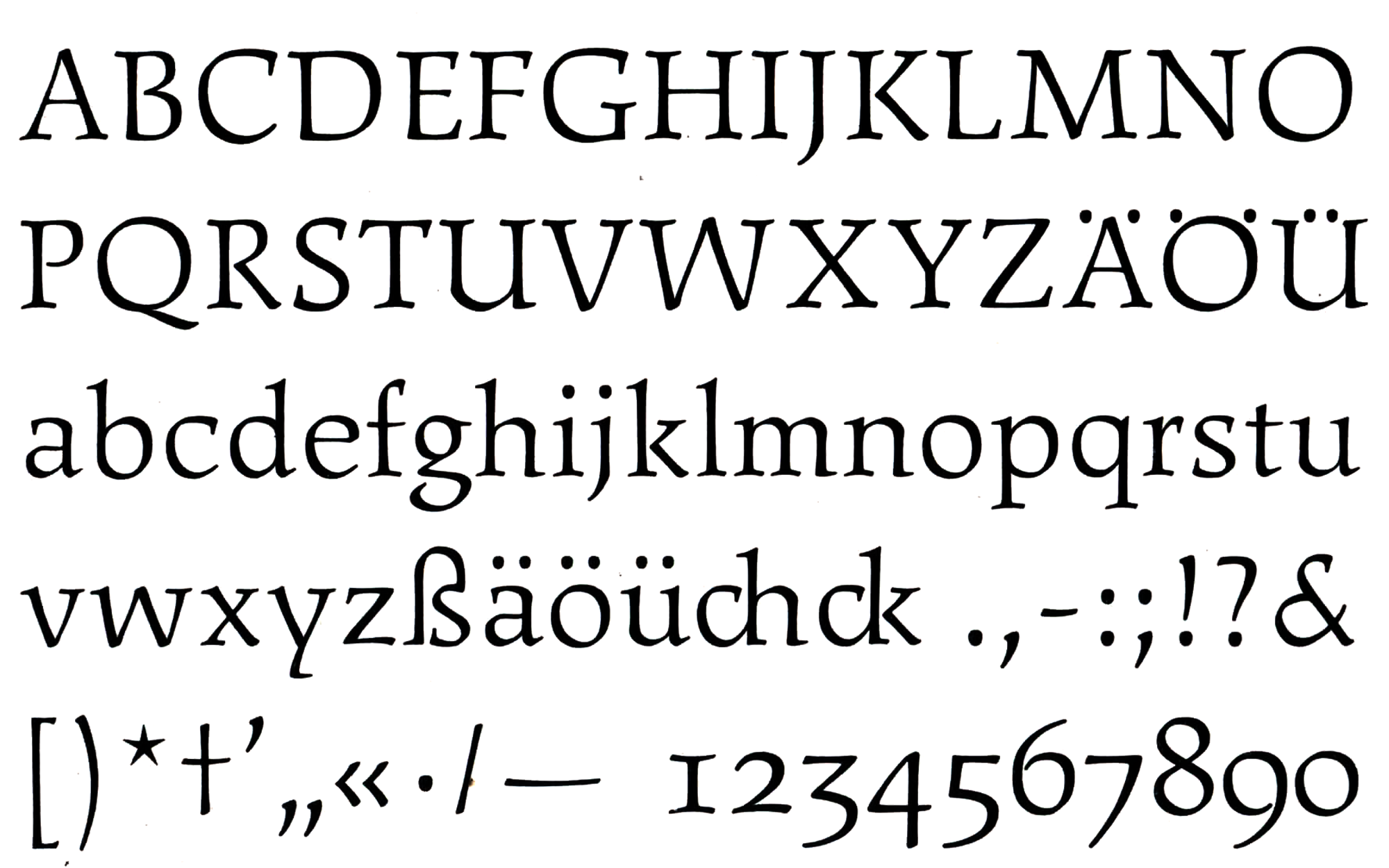
- circa 1960
- Antiqua humanistisch
Die Freundschafts-Antiqua bzw. auch Chinesische Antiqua wurde vom chinesischen Kalligrafen Li Yü Bing-nan während seines Studiums an der HGB entworfen. Ziel war eine Antiqua-Schrift, die im Satz mit chinesischen Zeichen kombinierbar war. Stilistisch ist die Schrift eine kalligrafisch-humanistische Antiqua, die sich mit offenen Formen und großzügiger Laufweite für Fließtext-Anwendungen eignet. Die Schrift wurde bei Typoart testweise geschnitten und gegossen und kam in der Folge auch zum Einsatz, ohne jedoch als Bleisatz-Schrift vertrieben zu werden. Entsprechend verweist dieser Eintrag auf die Produktion in den 1960er-Jahren, aber mit der Einstufung als »kein Vertrieb«.
Elsner+Flake nahm die Schrift auf Basis des Typoart-Materials als Bingnan-Antiqua auf und es existiert auch eine Digitalisierung von ARTypes als Freundschafts-Antiqua mit Kursiven. Eine umfangreiche Neubearbeitung wurde unter dem Namen Freundschafts-Antiqua Neue angekündigt, ist jedoch noch nicht erhältlich.